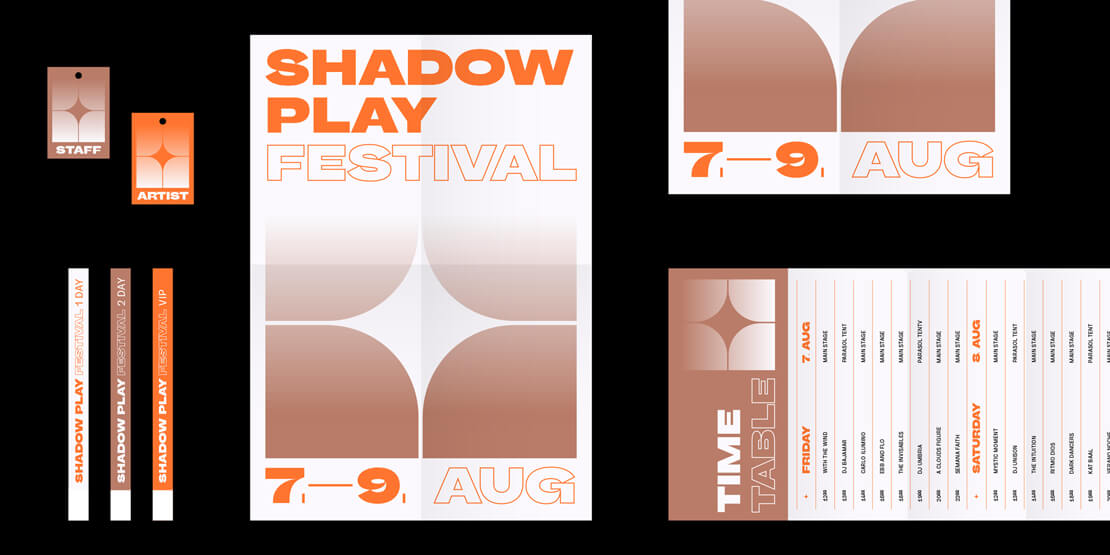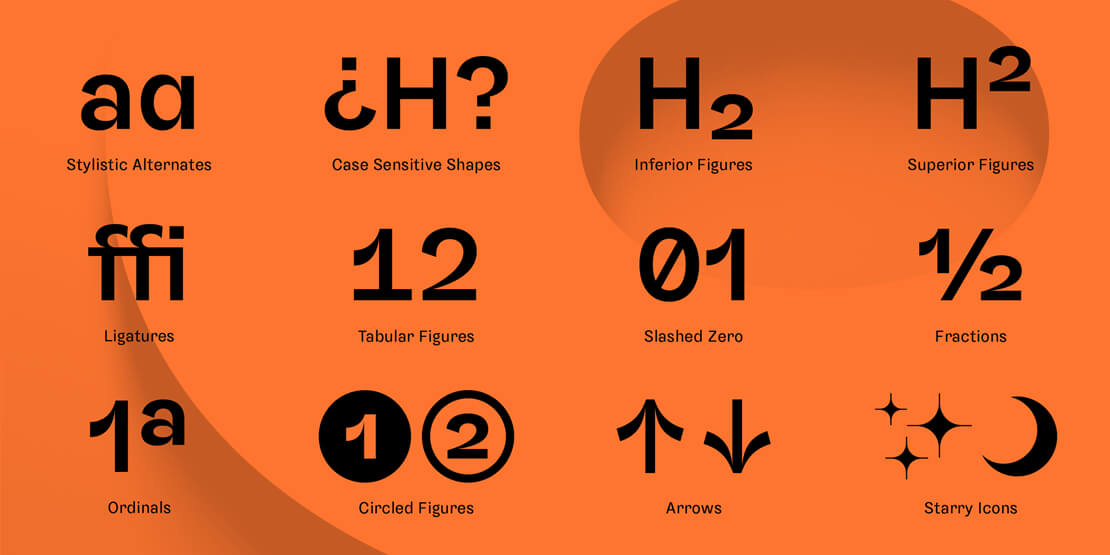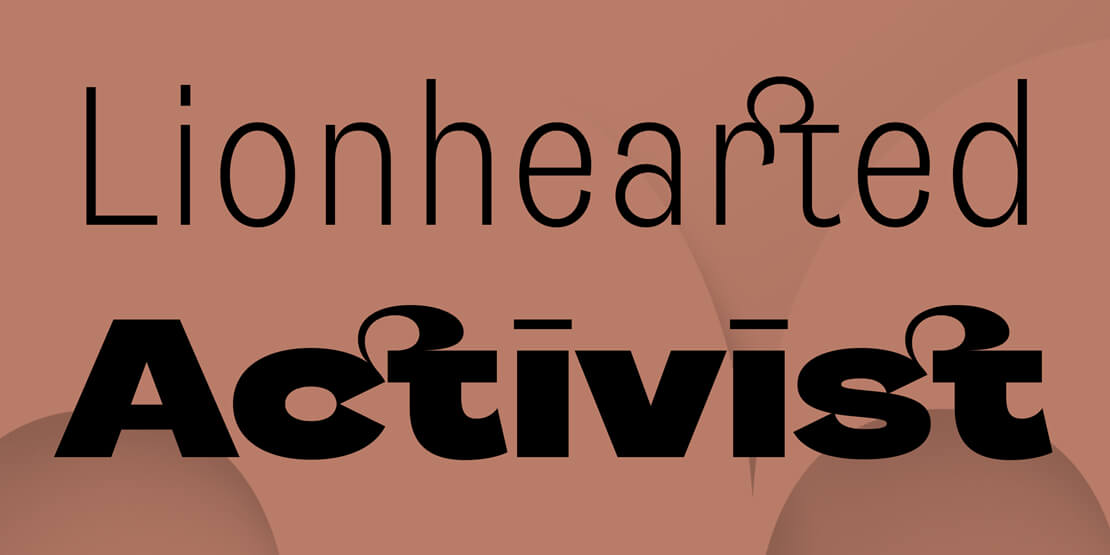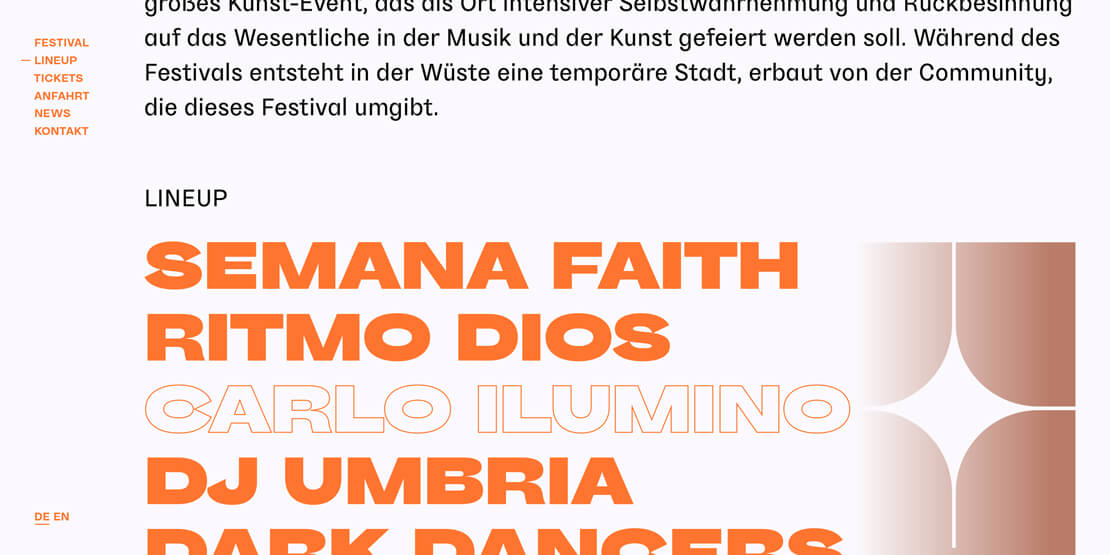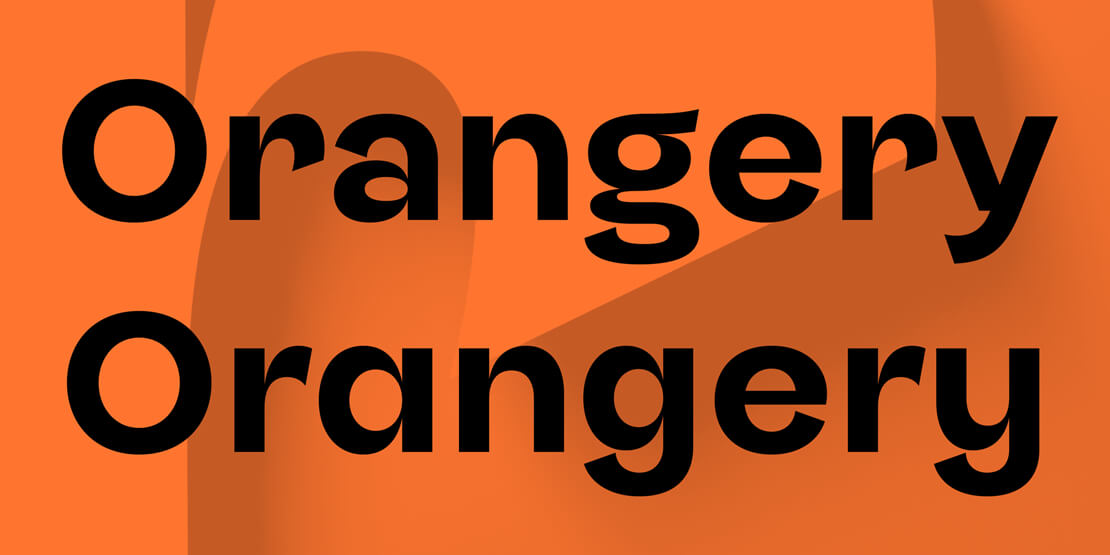
Sombra: organische Schrift mit florierender Dynamik
Die TypeMates präsentieren mit »Sombra« eine organische Schriftfamilie für Branding, Editorial und Packaging in Themenbereichen wie Natur, urbanes Leben, Kunst oder Kultur.
Sombra ist eine organische Groteskschrift mit florierender Dynamik, die von Paul Eslage gestaltet wurde. Die Schriftfamilie kombiniert ein geometrisches Grundgerüst mit organischen, scharf anschwellenden Strichenden und extremen Einschnitten.
Die Spannung zwischen dieser organischen Dynamik und der geometrischen Konstruktion macht sie zu einer markanten Schrift für Branding, Editorial und Packaging in Themenbereichen wie Natur, urbanes Leben, Kunst oder Kultur.
Sieben Strichstärken für anspruchsvolle Aufgaben
In sieben Strichstärken wächst Sombra von einem kompakten Light-Schnitt zu einer breitgezogenen Black und zeigt ihre eigenwillige Seite im tiefschwarzen Poster-Schnitt. Dieses ungewöhnliche Wachstum der Schnitte macht sie zu einer vielseitigen Option für anspruchsvolle typografische Aufgaben: Eine schmale Thin für kurze Informationen auf der Rückseite einer Verpackung, eine wohlproportionierte Regular für alle Arten von Mengentext und eine breite Black für Headlines.
Durch das zeitgleiche Wachstum von Schriftgewicht und -breite erzeugt Sombra beim Kombinieren von Schnitten außerdem eine visuelle Spannung.
Der Poster-Schnitt rundet die organische Schriftfamilie ab. Mit seinen zulaufenden Strichenden sowie der extra leichten Interpunktion und Sonderzeichen reizt der Poster-Schnitt Sombra’s ursprüngliches Design-Konzept aus und hebt sich vom Rest der Familie ab.
Umfangreiche Zeichensätze
Mit mehr als 680 Glyphen pro Schnitt unterstützt Sombra über 140 lateinische Sprachen und ist vollgepackt mit Pfeilen, Stern-Symbolen, umkreisten und hochgestellten Ziffern sowie ausgefallenen und Standard Ligaturen. Außerdem bietet die Schrift eine ganze Reihe an Stylistic Sets wie Alternativ-Buchstaben für schlichtere Mengentexte und Wortmarken oder hochgestellte Nachkommastellen für kompakt formatierte Preisangaben und Uhrzeiten.